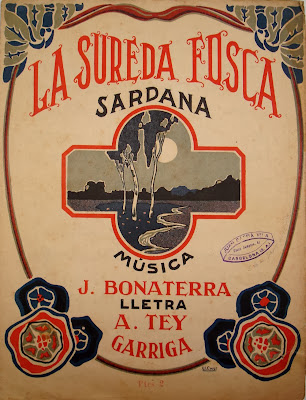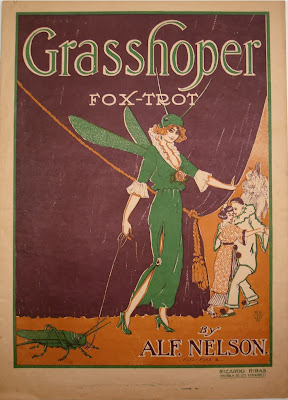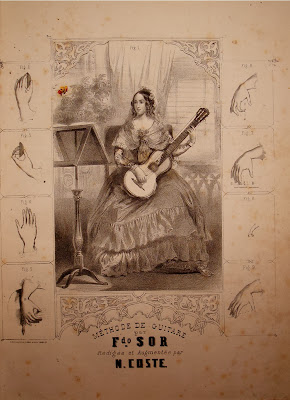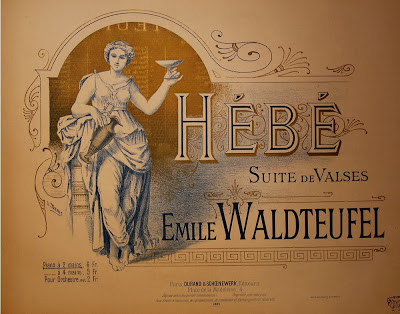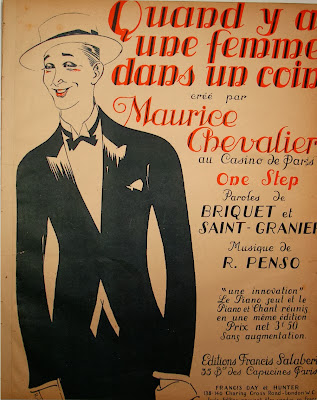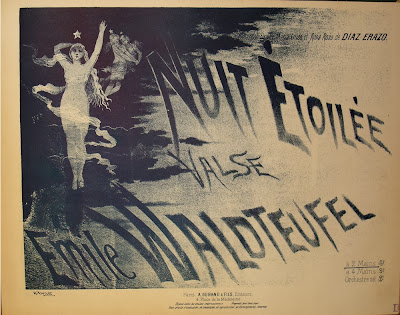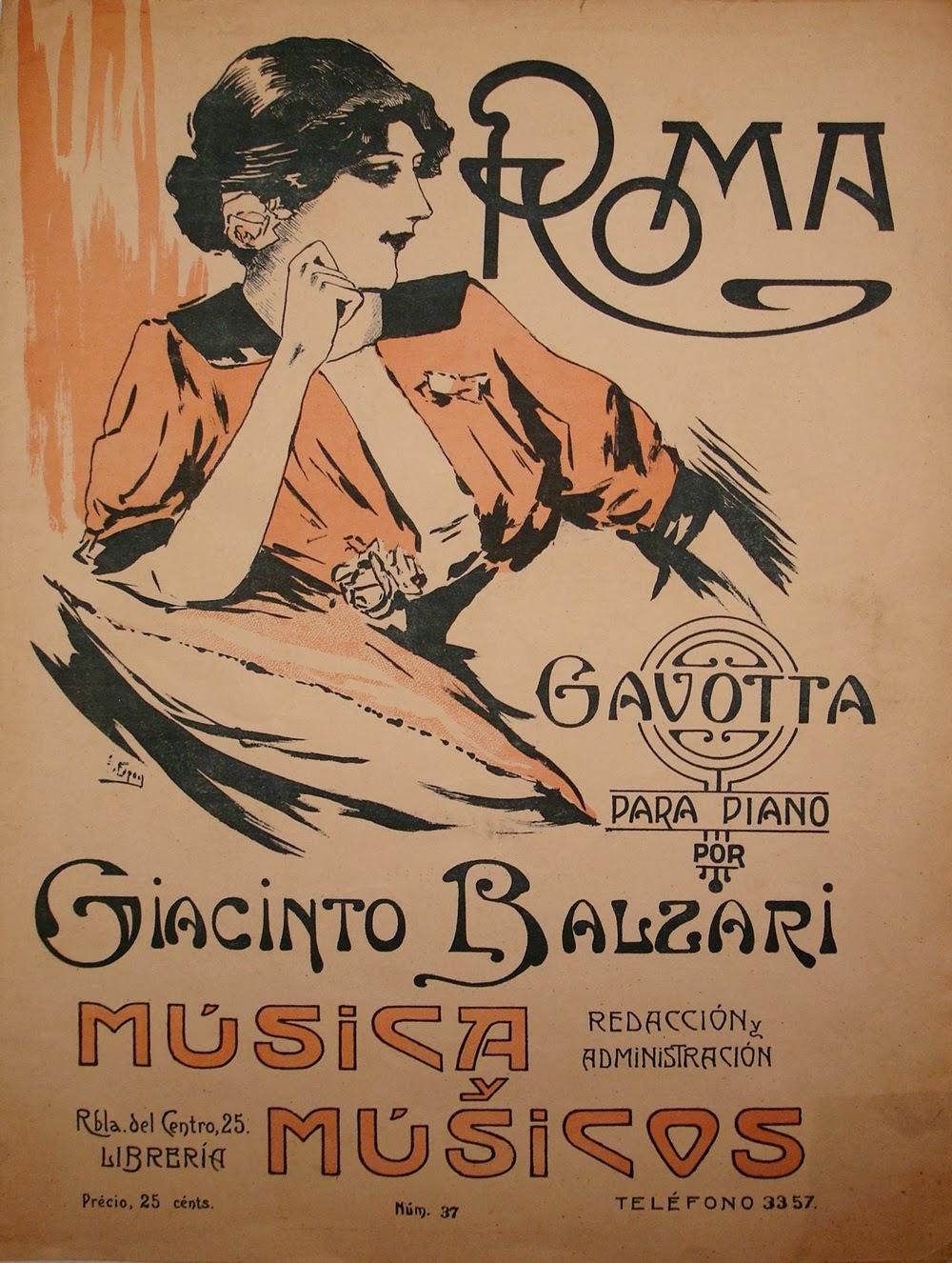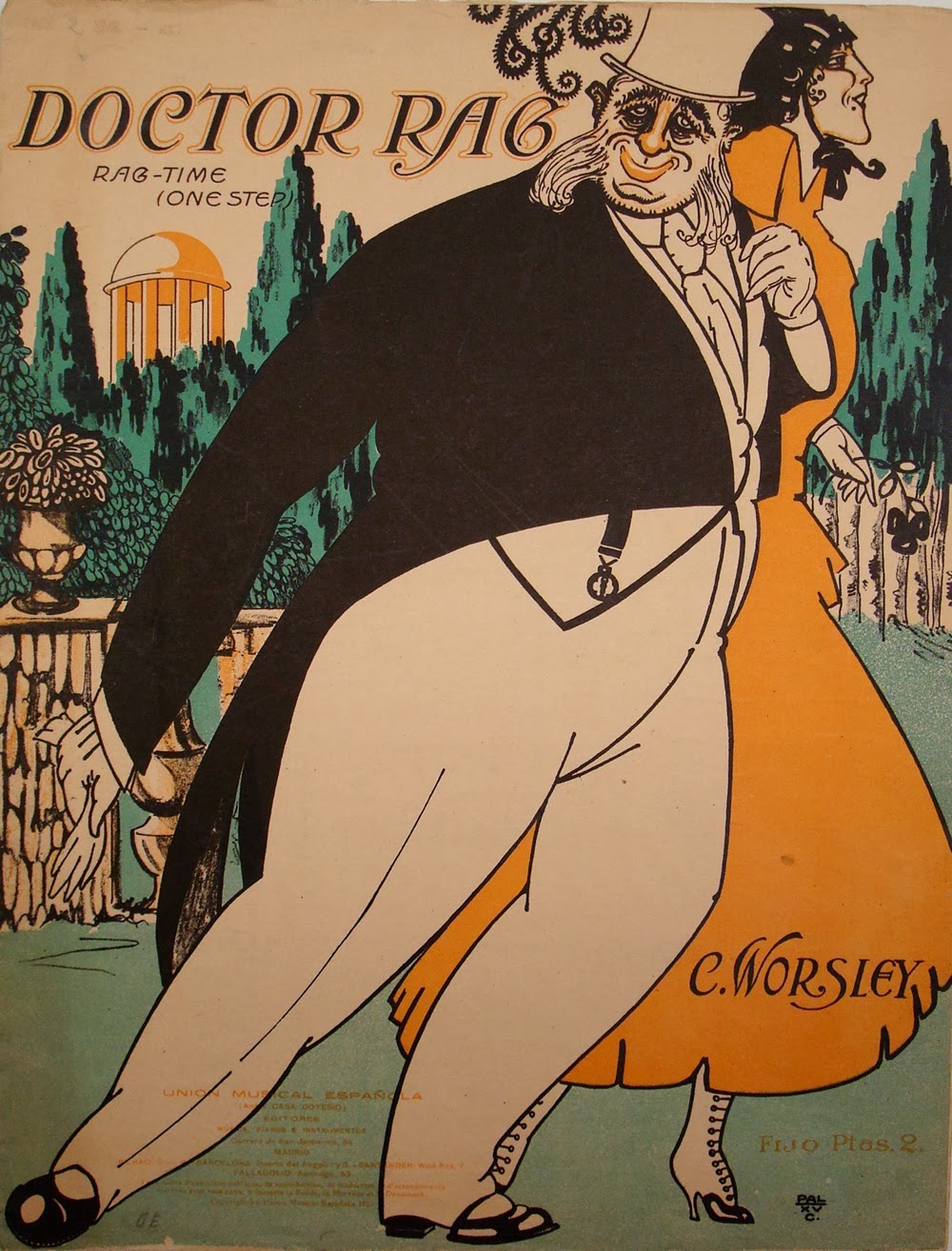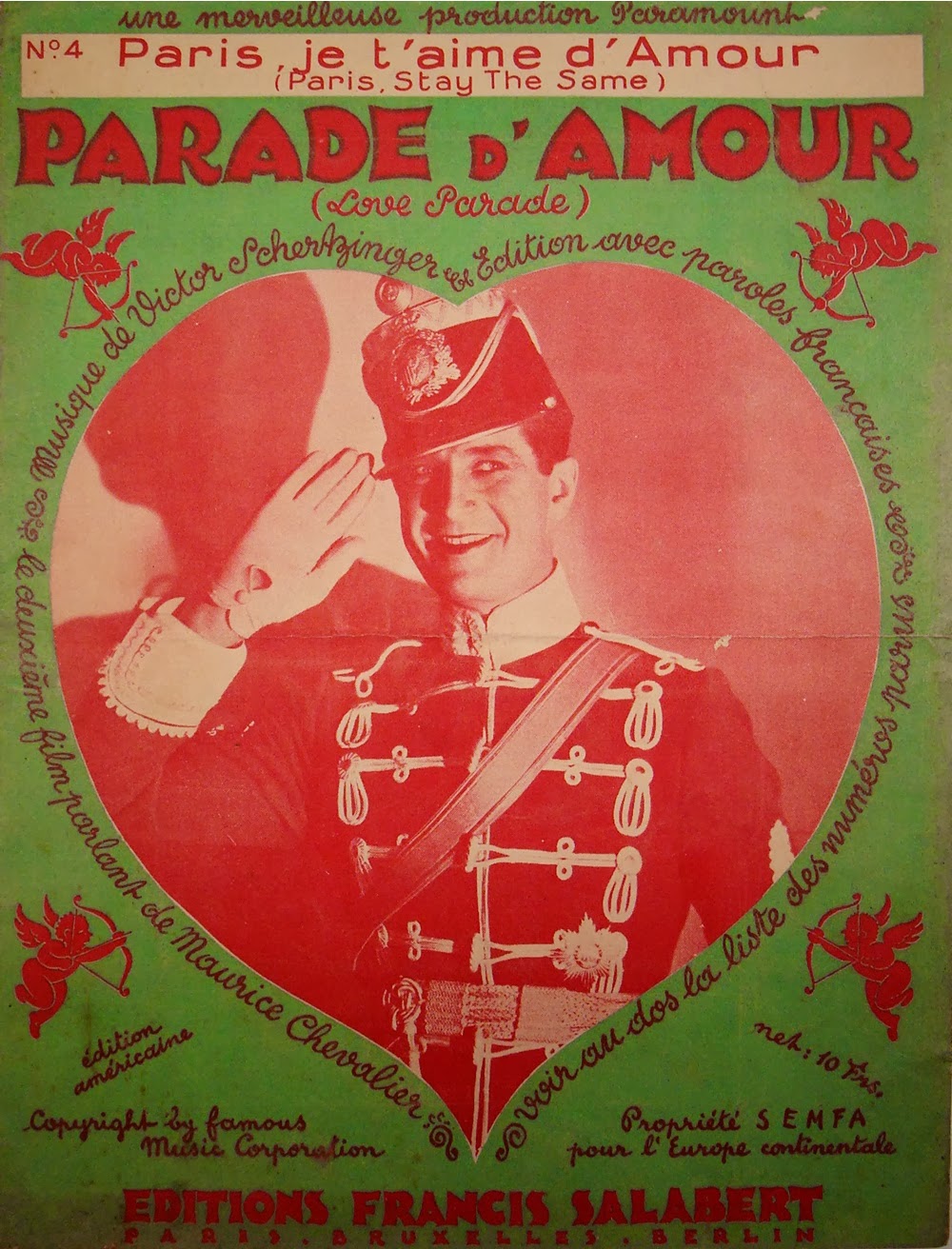
| Detalle portada de "Maruxa", música de L. Vives |
Como siempre hay algún que otro artículo en Bibliotypes que se sale un poco de los tema habituales. Este en concreto espero que os interese por el aspecto tipográfico, la ilustración y como no por la música.
Pocos trabajos son menos reconocidos que el hecho por numerosos diseñadores y artistas en el campo de la ilustración musical. Los estudios en la edición musical están centrados básicamente en: autores, interpretación, edición y tipografías, imprentas musicales, evolución del arte de la impresión musical, etc... pero pocos están centrados en la ilustración de las partituras y en la aportación que muchos artistas plásticos hicieron en este campo especialmente en el s. XIX y XX.
Actualmente existen webs especializadas en la ilustración de portadas de partituras como por ejemplo la maravillosa
ILUSTRED SHEET MUSIC COLLECTION que contiene mas de 10.000 scaners de portadas
. En temas de catalogación musical encontramos buenos consejos en la BNE ver
"Manual de catalogación de partituras del s. XIX" , será en este apartado que centraré este artículo y en alguna aportación mas tipográfica de algunas portadas.
| Detalle de tipografía de Delpech s XIX |
Un poco de Historia a marchas forzadas:
Exceptuando los libros manuscritos musicales de la edad media y del renacimiento, muchos de los cuales son maravillas no solo musicales si no auténticas bellezas del arte de la caligrafía y del dibujo, la edición musical en los primeros siglos de la imprenta fue un arte dedicado solo a la estampación de la música y con muy poco o digamos nulo afán de belleza visual o estética. La posibilidad de poder editar la música en España en los primeros siglos de la imprenta es muy complicada y está localizada solo en algunas imprentas por esto muchas obras musicales se publicaron en el extranjero. Este problema perduró hasta el s. XVIII. (Dos ejemplos de ello: las célebres "Ensaladas" de Mateo Flecha (1481-1553), las editó su sobrino en Praga en 1581 y el método de violín del autor español, Joseph Herrando, esta publicado en castellano en París el 1756)
En el s. XVIII encontramos ya algunas partituras impresas con la intención de embellecer la edición tanto en la tipografía como en conjunto visual de la partitura. Uno de los ejemplos mas claro en este sentido es "The Musical Entertainer" impreso por Georg Bickham en Londres desde 1736 hasta 1740. Este celebre impresor, autor también de la célebre obra caligráfica "Universal Penman", es considerado el autor del libro musical mas bien ilustrado del s. XVIII. Este libro reúne una serie de danzas y canciones de los dos mas afamados compositores del Londres del periodo barroco: Purcell y Haendel. El libro está pensado para agradar y ser más una joya bibliográfica para la corte y la nobleza de la época que un libro para la difusión y servicio a la música. Todo el libro está enteramente grabado y se utiliza la escritura caligráfica para la letra.
| Portada de "The Musical Entertaiment" de G. Bickham |
En España encontramos algún ejemplo mas modesto pero digno de mención, como es la obra del polifacético, grabador Pablo Minguet e Yrol, autor de varias obras de múltiples temáticas entre ellas la música. La obra en cuestión es la "Academia Musical de los instrumentos..." Madrid: Joaquín Ibarra, 1754.
Estos pequeños manuales de como tocar los instrumentos son en algunos casos, como por ejemplo el violín, los primeros publicados en España sobre el tema.
| Portada "Academia musical de los instrumentos". P. Minguet, 1754 |
Ejemplos de algunas láminas de grabados al cobre, sobre guitarra, psalterio violín y flauta travesera:
| "Demostración de los puntos de la guitarra", P. Minguet , 1754 |
| "Demostración y diapasón del Psalterio", P. Minguet , 1754 |
| "Escala de G Sol re ut por el violín", P. Minguet , 1754 |
| "Escala...de la flauta travesera", P. Minguet , 1754 |
| "Au Clair de la Lune..." Barbizaet, s. XIX |
Ya dentro del s. XIX encontramos también publicaciones del tipo almanaque para señoras en que encontramos colecciones de canciones y poesía, con cuidadas encuadernaciones y bellos diseños tipográficos y grabados.Como ejemplos vemos " le Ménestrel Français" circa de 1820, y " L'Echo des Bardes" de 1882.
Bonitas encuadernaciones de piel con estuche,
decoradas con dorados y gofrados del s XIX |
Portada del Almanaque musical:
" Le Ménestrel Français" circa de 1820
Canción del Almanaque musical:
" Le Ménestrel Français" circa de 1820 |
Portada del Almanaque musical:
"Echo des Bardes" 1820 |
Canción del Almanaque
"Echo des Bardes" 1820 |
| Detalle portada de "Crépuscle" música M. L. d'Orsay |
La mayoría de obras musicales partituras, métodos etc hasta 1850 tenían una portada tipográfica con mas o menos esmero y algunas añadían una grabado o ilustración con la intención de ilustrar algunas cosas básicas del temario de la obra. Vemos ejemplos:
- Portada, grabada al cobre, del célebre método de forte-piano de Pleyel y Dussek (1797):
| Portada del método de forte-piano de Pleyel- Dussek, 1797 |
- Méthode de Harpe de Bochsa et fills. Paris: Schonenberger, 1830 c.a. Las ilustraciones de este libro ya son litografías.
| Posición para tocar la arpa, Méthode de Harpe de Bochsa, 1830ca. |
- Gran Método elementare de violino, Francisque Alday. Torino: Giudici e Strada,1830 ca. (No estoy seguro del procedimiento de estas ilustraciones, dudo si aún son grabados al cobre?)
| Detalle de "Roma" de Giacinto Balzari |
| Detalle de un diseño de Emili Ferrer |